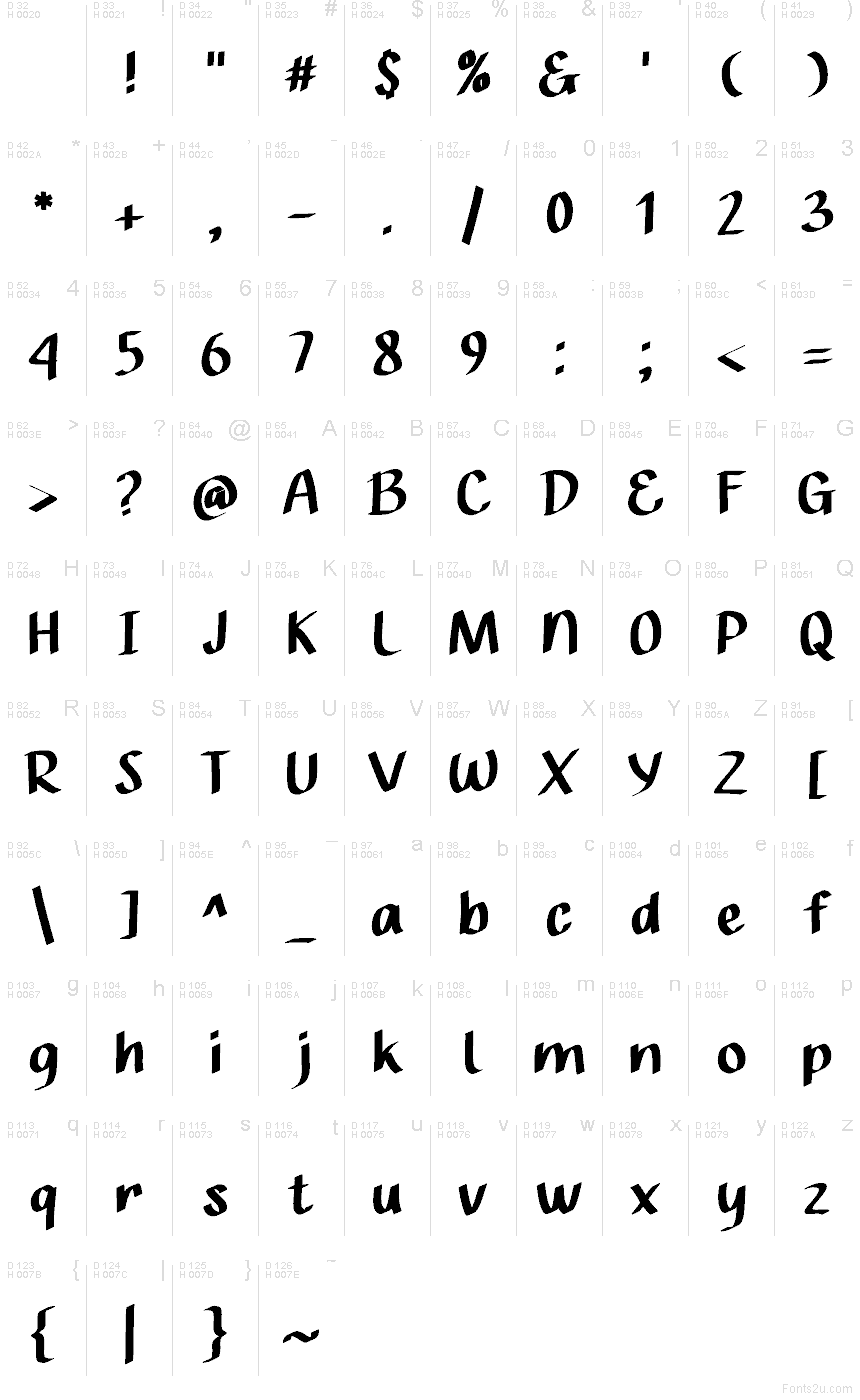
Terneuzen
Шрифтова гарнітура Terneuzen від Hello Good Studio — це безкоштовний пензлевий шрифт із нахиленими рукописними штрихами, гострими закінченнями та широкими вигинами, що надають літерам живописного, дещо нерівномірного ритму. Форми виглядають енергійно та прямолінійно, а достатній контраст штрихів робить напис живим, не перевантажуючи його.
Terneuzen чудово підходить для логотипів, меню кав'ярень, постерів, пакування товарів та графіки для соціальних мереж, де органічно виглядає ручний пензлевий стиль. Цей безкоштовний шрифт додає необхідної динаміки коротким заголовкам або підписам, залишаючи при цьому простір для ілюстрацій чи фотографій.